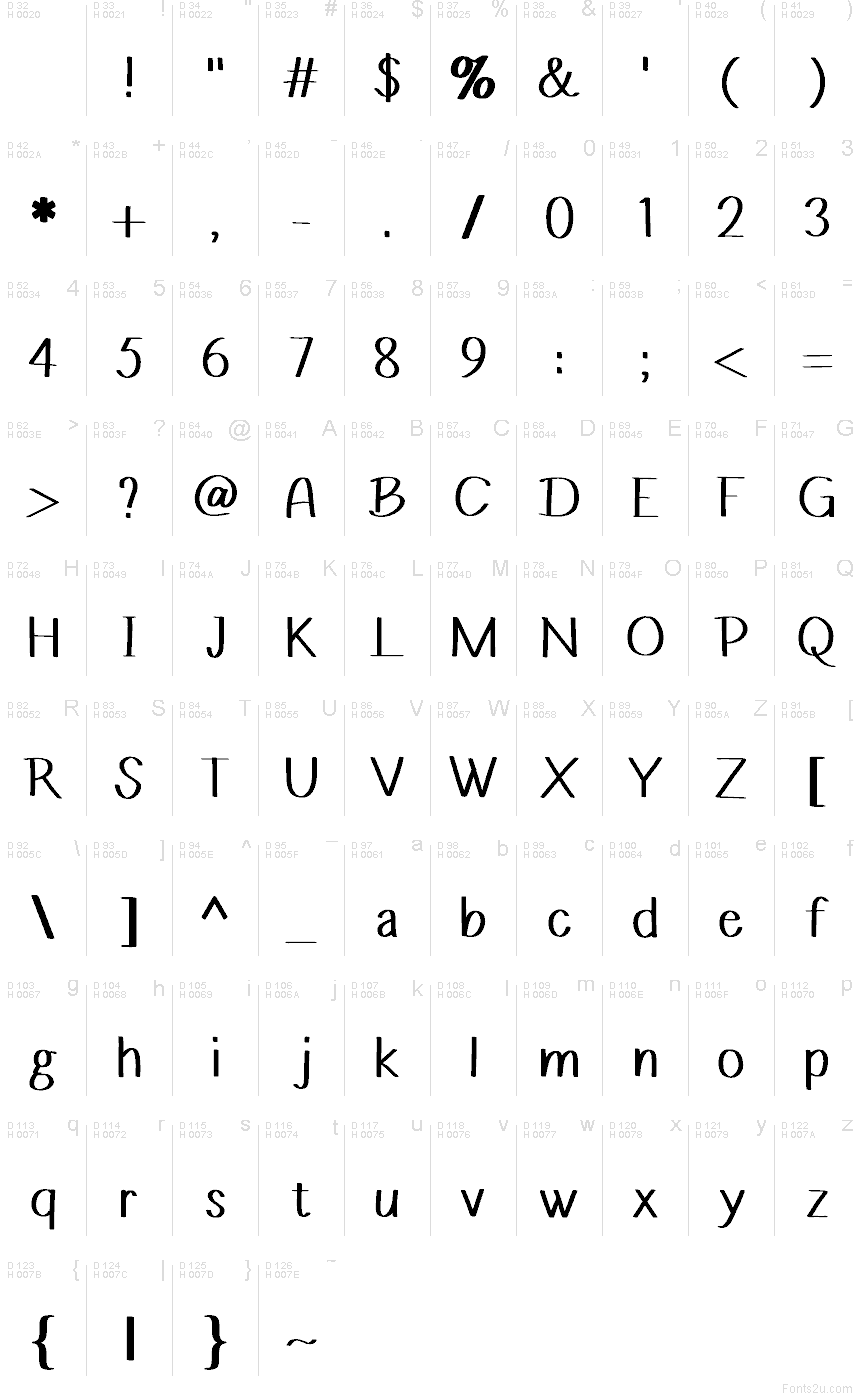
Dana N Tara
Dana N Tara від Hello Good Studio - це безкоштовний рукописний шрифт із високими каліграфічними засічками та легким, невимушеним ритмом «від руки». У літерах поєднуються тонкі гострі штрихи, плавні вигини та конічні з'єднання, що надає дизайну витонченого та індивідуального характеру, не перевантажуючи його зайвими деталями.
Dana N Tara чудово підходить для запрошень, логотипів, графічних цитат, упаковки товарів та брендингу бутиків, де рукописний акцент важливіший за суворі друковані шрифти. Цей безкоштовний шрифт також ідеально впишеться у вітальні листівки, редакційні врізки, етикетки та короткі графічні пости для соціальних мереж, оскільки його плавні форми додають крафтової, людської теплоти невеликим блокам тексту.